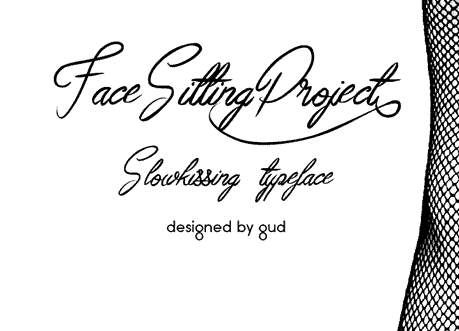
Face Sitting Project Font – Download Grátis
A Font ‘Face Sitting Project’ é uma criação única, escrita à mão que nos apresenta um estilo deslumbrante e versátil. Inspirada por sentimentos autênticos de personalidade, esta font oferece uma experiência visual verdadeiramente emocionante aos designers que buscam adicionar algo especial a seus projetos digitais. Desenvolvida pela designer 178-MC, esta font é ideal para quem busca um touch único e vibrante em suas criações. Ela pode ser usada gratuitamente para fins pessoais, mas a recomendação é usar-a de forma comercial pelo site especializado http://www.revolge.com/product/facesittingproject/. Para qualquer dúvida ou contato relacionado à fonte, você pode entrar em contato diretamente com o autor através do e-mail . Seja para uso em logotipos, designs gráficos pessoais ou até mesmo como parte de uma nova estratégia de marketing, a ‘Face Sitting Project’ está aqui para tornar sua arte digital um pouco mais autêntica e emocionante.